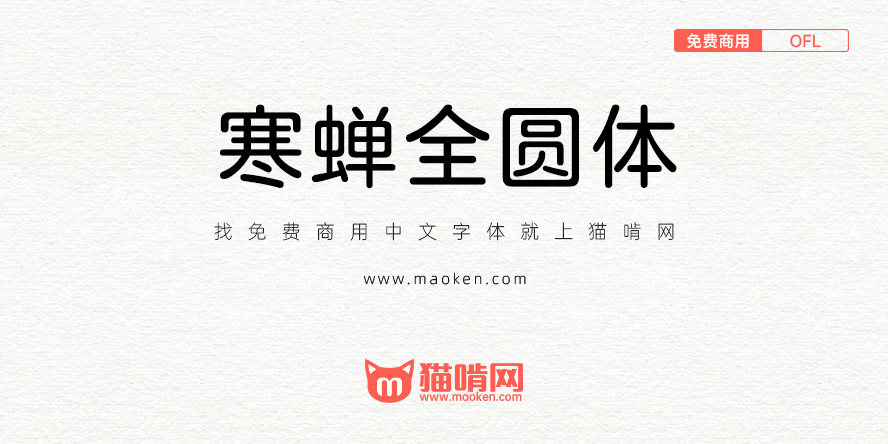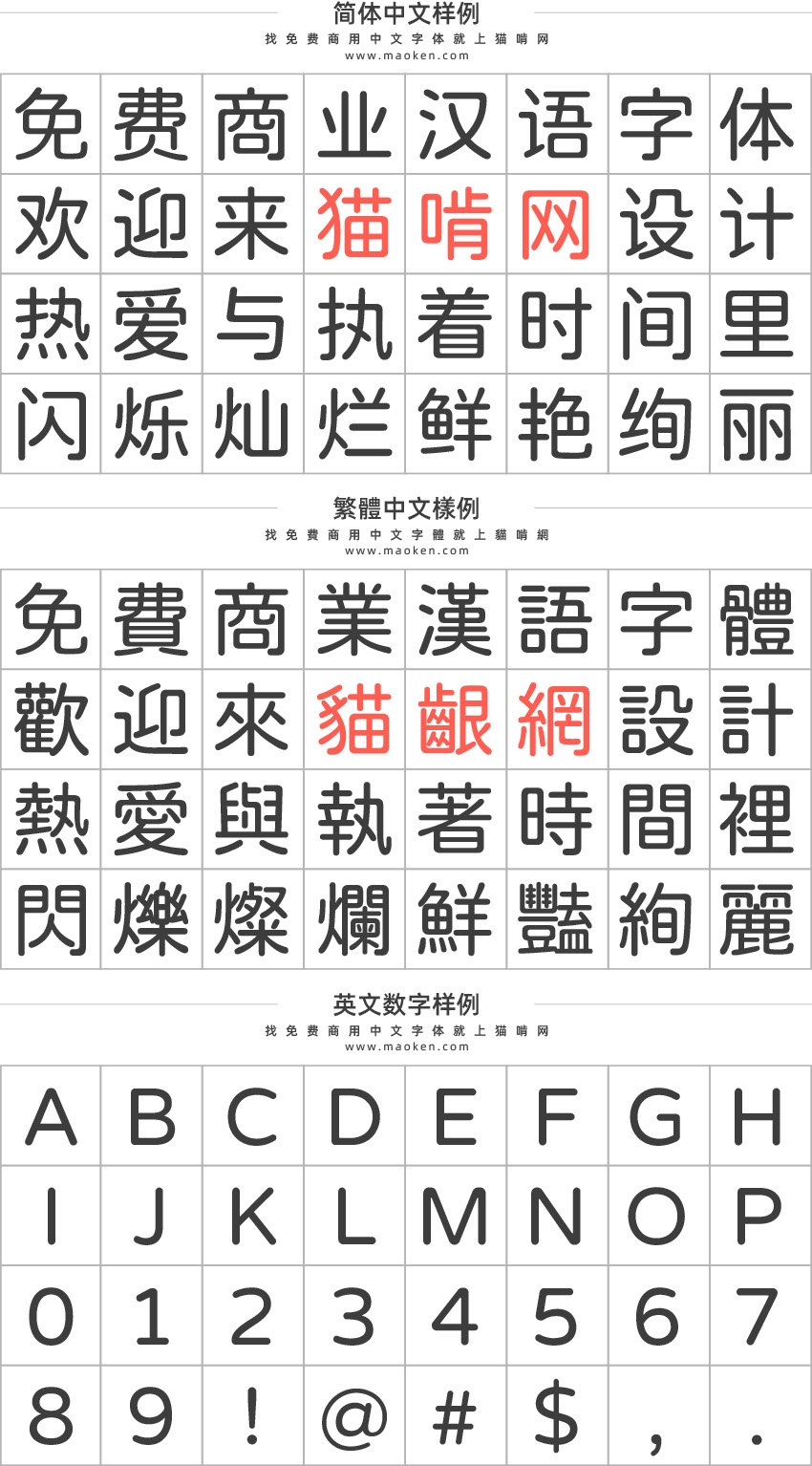
寒蝉全圆体:基于日本开源字型小杉圆体进行调整的圆体字型
Ver 3.200(2024/05/09)
• 01 对于“#4”“#5”提到的问题进行修复,遍历所有字符形,修复所有字体曲线方向不一致导致的问题。
• 02 重磅更新:增加粗体版本。曲线轮廓调整并针对横画过多的笔画进行了特别调试。
• 03 调整若干字形。
Ver 3.102(2024/01/08)
• OpenType特性自由合字更新:
输入“喜喜%”为“囍组合”,输入“再见%”为“再见组合”。输入“笑死%”为“笑死组合”
• 修复字符ふ㋋
• 调整字形萠含唅晗焓商墒熵言信訇訚唁狺這詈詹誉誊誓燮謇謄謦警譫譬譽讐
• 新增字形朤䜣亖
Ver 3.1(2023/11/15)
Ver 3.0(2023/08/11)
• 寒蝉全圆体更新3.0版本
Ver 1.5(2023/03/10)
• 寒蝉全圆体更新1.5版本
Ver 1.000(2023/03/10)
• 寒蝉全圆体发布
这个是目前完成度最高的一款字体,唯一缺点:数字太大太宽~~~~
挺喜欢这个字体的,但这个字的“空”,是日本字形,不是中国大陆标准字形,一些笔画也不是中国大陆字形的
• 基于日本开源字体改的
为什么这款字体的数字不等宽了?
半圆太圆,全圆正好。唯一一点就是感觉数字太大,占用宽了些。要是半圆的数字英文就好了
适合阅读,省眼。
测试了一下自己补粗和常规下载的粗细,目前在手机上使用的时候,货物的货字会因为系统加粗而导致左上角的七显示极细,但是fontcreator里面字体没有出现显示问题
• 字体曲线方向不一致导致的问题
ふ左侧的点会变大
很完美,要是能增加个粗点的字重就好了
小写的 g 下面显示不全
《滕王阁序》俨骖騑于上路的騑。感觉这是绝对的不常用字,马字旁都是繁体的,但是又因为滕王阁序变成了不那么不常见的字……
• 甚至《通用规范汉字表》也收录了这个「𬴂」字(简体「𬴂」的 Unicode 是 U+2CD02(Ext E)
• 可惜我不太喜欢这个字形的写法;还是偏向于真正的国标字形……
非常棒,希望可以增加字重,以及竖排标点(感叹号和问号)希望可以居中
值得一提的是,台湾设计师在2020年3月14日发布一款小杉圆体的改进版本JustFont粉圆字体,而猫啃网基于JustFont粉圆字体发布了补了简体字的猫啃网糖圆体,中国大陆的小伙伴推荐使用猫啃网糖圆体。
• 看需求,猫啃的简体汉字保留了一定的繁体汉字风格,还有个保持更多日文汉字风格的传承糖圆体,这个简体汉字是完全按简体的写法来了。